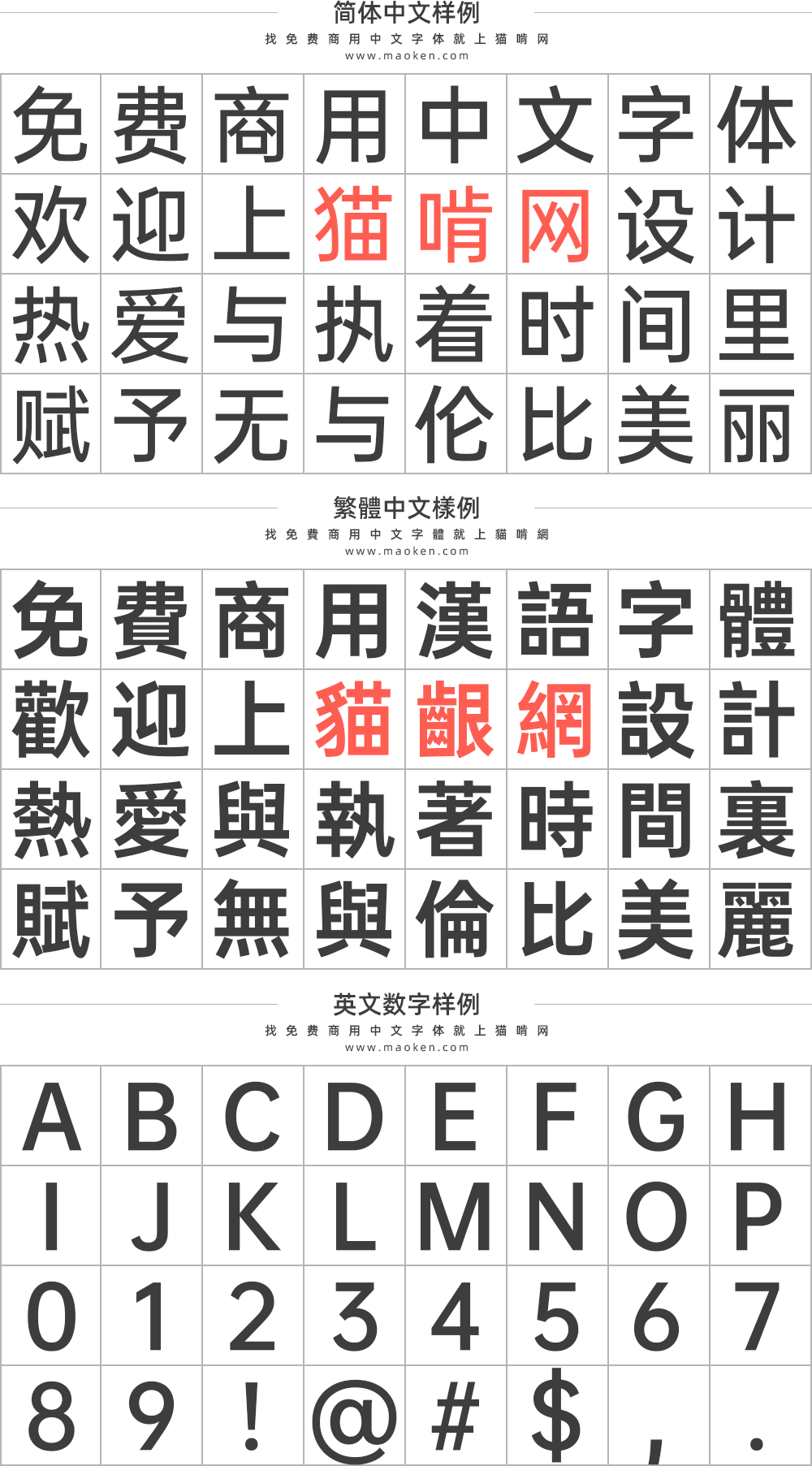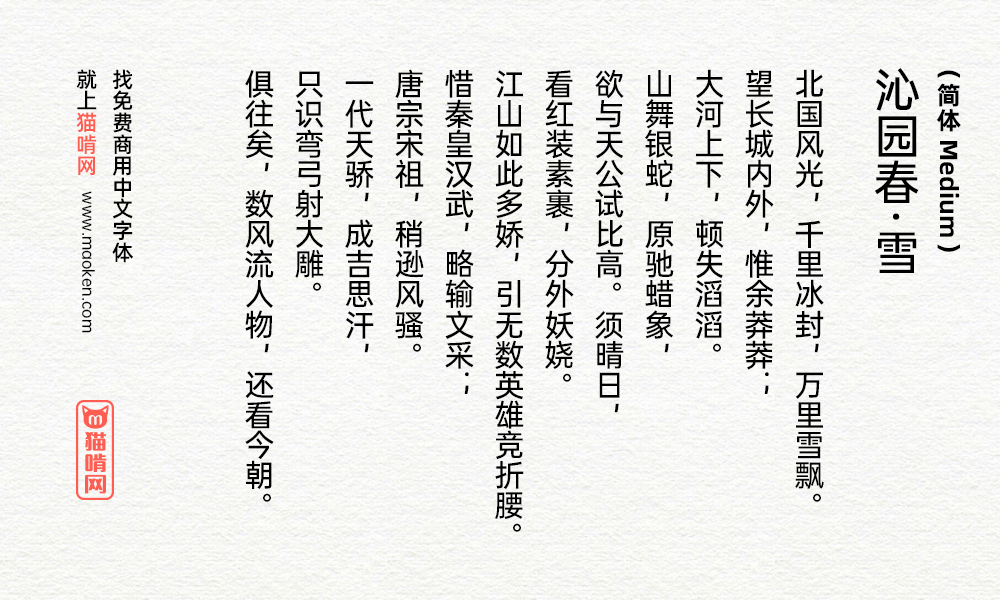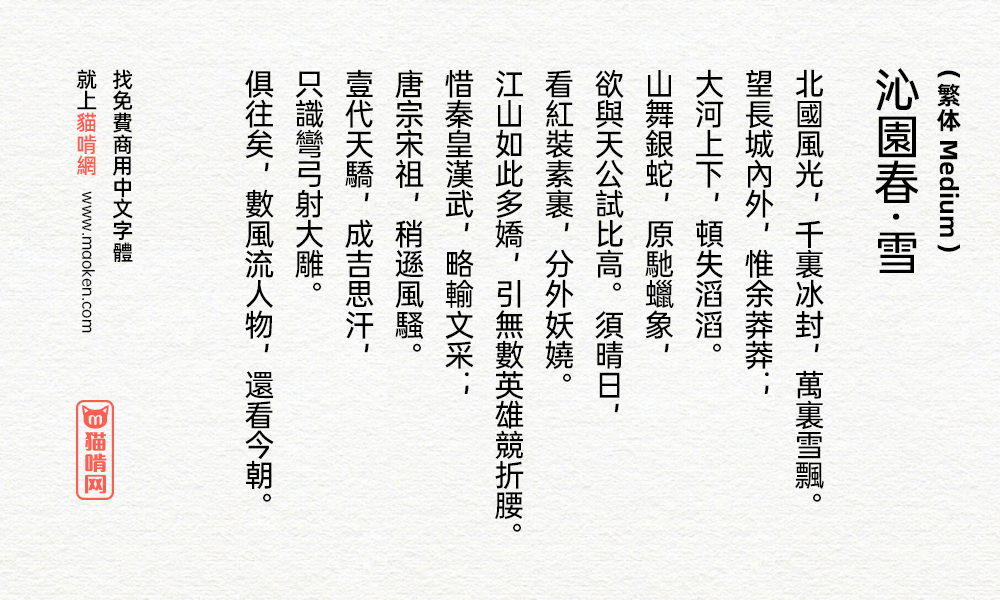
OPPOSans品牌字体:科技美感探索精神全球视野
字体作者:OPPO (中国大陆) 字体字重:5个
字体背景
2019年11月20日,在OPPO第二个十年的开端,OPPO希望从产品到品牌都能为用户带来全新的体验。所以,全新的OPPO Logo应运而生,它化繁为简,更加包容。除此之后,还伴随着一套属于OPPO的品牌字体诞生,那就是「OPPO Sans」,它针对移动端做了很多像素级的优化,长时间阅读也不累。
「OPPO Sans」中文部分由汉仪字库字体设计总监朱志伟指导,黄珍元设计完成,西文部分则由美国Pentagram五角公司设计,汉仪字库西文项目组负责人张暄协作完成。OPPO品牌字体紧随品牌升级的步调,从品牌理念出发,用文字全方位探索科技美感,用独特的语言打造具有标志性的、与众不同的品牌字体。
字体特色
「OPPO Sans」是OPPO全新的品牌定制字体,首发于ColorOS 6操作系统,OPPOSans采用了全新骨架,中宫自然舒适,结构稳定,字形舒展,视觉重心的提高,让整体造型看起来挺拔优雅,充满生命力。这套字体体现了“简洁真实”的OPPO品牌追诉,简化笔画,让字体看起来更加简洁、干净,在提高屏幕显示的阅读体验的同时,也能够释放OPPO现代化科技美感。
OPPO Sans 家族字体包括Light / Regular / Medium / Bold / Heavy ,OPPO Sans 西文部分,沿袭了新 Logo 中外扩的圆形曲率,将其完美融合在文字体设计之中,共覆盖21个国家语言,共11个语种。
字体设计理念
OPPO Sans提高了视觉重心,并设计了全新的骨架,重心部位自然舒适,字形更加舒展,整体结构稳健。
化繁为简 简洁真实,简化笔画的同时更有科技感。
“简洁真实”是 OPPO 追诉的品牌美学,简化笔画,在提高屏幕显示的阅读体验的同时,也能够释放 OPPO 现代化科技美感。把握更多的细节处理,例如去除出脚,让「OPPO Sans」看起来更加简洁、干净。
曲线处理更加光滑流畅、柔和,更具现代感和未来感。 在曲线处理上更加光滑,简洁而富有变化,更体现曲线的流动之美。
角度处理上比较柔和,收尾干净利落。
然而OPPO的野心越来越大,准备打造一个全球化的品牌,字体也是战略部署的一部分,共覆盖21个国家语言,和11个语种。